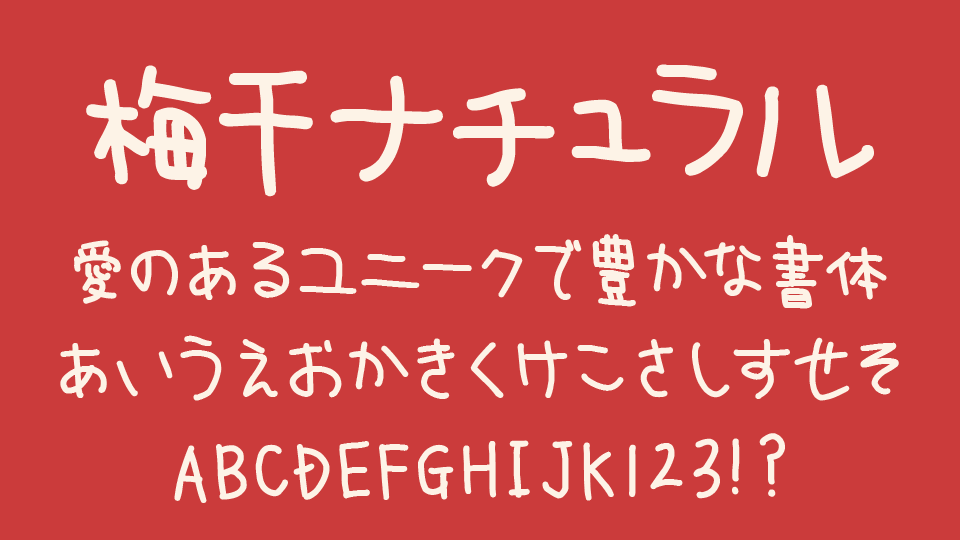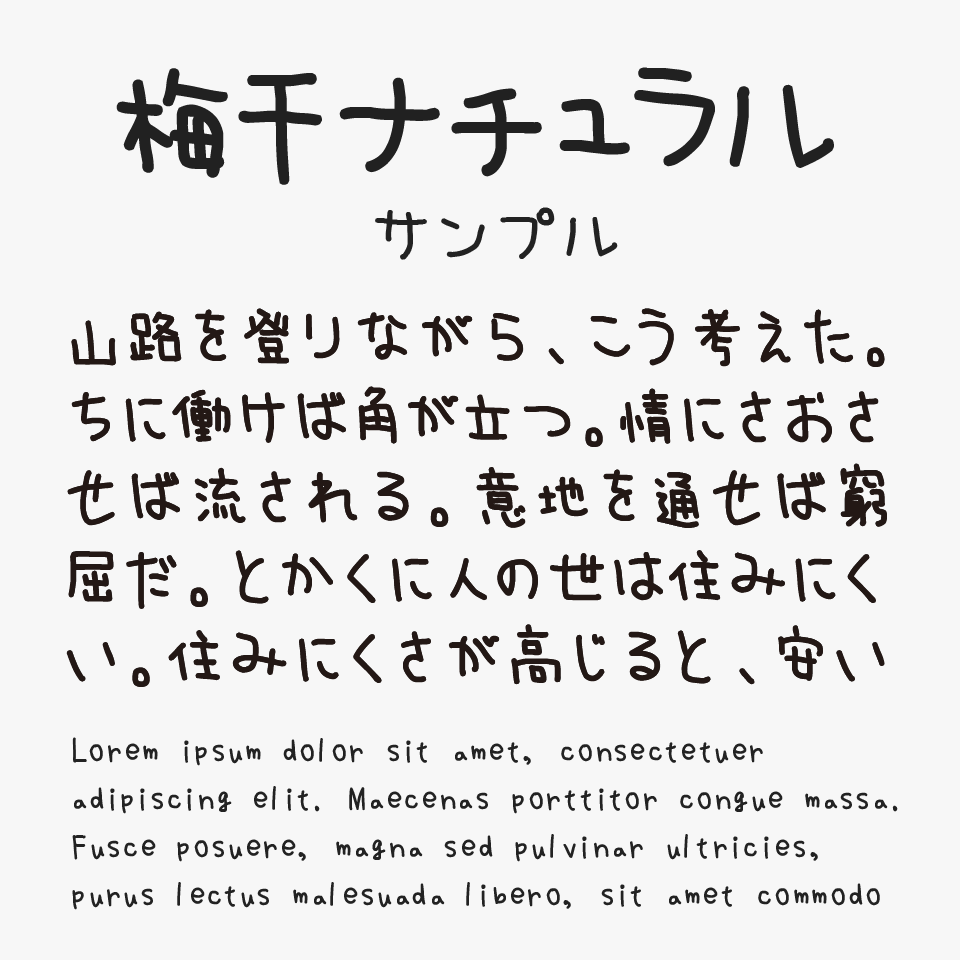
梅干ナチュラルフォントは、「文字サイズやバランス等を一切無視」して制作されたリアルの書き文字感がステキな手書きフォントです。
線の太さや文字の大きさにわずかなムラがあり、実際にペンで書いたようなナチュラルな温かみを感じられるフォントです。力を入れすぎていないラフな雰囲気がありながらも視認性は高く、気軽に使いやすいバランスの良さがある手書きフォントです。
メッセージカードやSNS投稿、ブログアイキャッチ、同人誌、カフェメニューなどにぴったりなフォントです。堅苦しさのない柔らかな空気感を演出できるため、ナチュラル系のデザインや手作り感を大切にしたい場面と相性抜群なフォントです。
梅干ナチュラル
梅干ナチュラルフォントを、ほかの太めで可愛らしい手書きフォントと比較してみると、親しみやすい“自然体の可愛らしさ”が特に魅力に感じるフォントです。
比較フォントは、「梅干フォント」「壱城ラウラ」「全員集合ポップ体」「ちはや純」「れいこフォント」と使用していますが、どれ可愛らしい手書きフォントなので、ぜひあわせてチェックしてみてください。
梅干ナチュラルと、「梅干フォント」「壱城ラウラ」「全員集合ポップ体」「ちはや純」「れいこフォント」を比較
収録文字は、漢字(JIS第一〜第三水準漢字)・ひらがな・カタカナ・アルファベット・数字・記号が収録されています。